<年末年始の挨拶状に>筆文字シリーズのご紹介(17/12/01)
モトヤでは、年末年始の挨拶状に最適な筆文字シリーズを各種取り揃えております。
書体が変われば印象もグッと良くなります。この機会に定評あるモトヤの筆文字はいかがでしょうか。
モトヤ筆文字シリーズ 各書体概要 (書体の成り立ちなど、詳細は文字の解体新書をご覧ください)
|---|---|
| 新楷書 | |
| 大楷 | |
| 隷書 | |
| 行書 | |
| 古印体 | |
| 教科書体 |
モトヤ仮名フォント・数字フォント・新聞明朝2・新聞ゴシック3
OpenTypeフォント発売のお知らせ(17/10/02)
株式会社モトヤでは、「仮名フォント・数字フォント・新聞明朝2・新聞ゴシック3
<仮名フォント>
モトヤの仮名書体は、個性あふれる23書体をラインナップ。
仮名を変えるだけで、文章の表情まで変わって見えます。
<数字フォント>
モトヤの数字書体は、90書体208種類におよぶバラエティ豊かな内容です。
簡単便利に使える記号類も全書体に収録しています。
<新聞書体>
モトヤの新聞書体は、全国紙をはじめブロック紙、地方紙など数多くの導入実績があります。
紙面上での濃度むらが少なく、可読性に優れています。
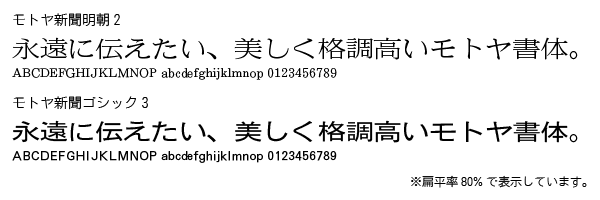
【組込み製品】モトヤARIB対応フォント発売のお知らせ(17/09/11)
モトヤの新製品「モトヤARIB対応フォント」の発売についてお知らせいたします。
株式会社モトヤでは、2017年9月11日に「モトヤARIB対応フォント」の販売を開始いたしました。
ARIB STD-B62規格は、一般社団法人電波産業会(ARIB)が策定するJIS X 0213:2004を標準文字セットとし
4K・8Kなど最新のデジタル放送向け記号・文字を追加した最新規格です。
モトヤでは、ARIBの最新規格である「ARIB STD-B62」に対応したフォントをラインナップしています。
高画質デジタル放送で読みやすく美しいモトヤフォントをご利用ください。
<書体サンプル>
| ○製品名 | モトヤARIBシーダ 3/5 モトヤARIBマルベリ 3/4 |
| JIS X0213:2004対応フォント | JIS2004対応フォントが新たにUD対応 |
| モトヤARIB対応フォント | 4K・8K対応ARIB規格STD-B62準拠フォント |
| ビットマップフォント | 組込み用UDビットマップフォント |
| モトヤフォントの導入事例 | 組込み機器などモトヤフォントの導入事例の紹介 |
モトヤLETSの新書体「アラタ2B/4/6」ダウンロード提供のお知らせ(17/08/08)
モトヤLETS会員様向けの新書体としまして、「モトヤアラタ2B/4/6」のダウンロード提供が
2017年8月22日より開始されます。
今回、提供が開始されます「モトヤアラタ」は、仮名フォント「Mkアラタ」のレトロな雰囲気はそのままに、
「Mkアラタ」が持つエレメントの特徴を持った漢字を収録し、さらに仮名をリデザインした書体です。
和文書体として帰ってきた新たな「アラタ」書体、3ウエイトの登場となります。
<書体サンプル>
○提供書体:モトヤアラタ 2B/4/6
Windows10アップデート後の不具合に関するお知らせ(17/01/05)
Microsoft社から提供されているWindows10の大規模アップデート「Anniversary Update」を適用すると、主にOpenTypeフォントでの縦組みにおいて複数のアプリケーションソフトウェアで表示や印刷で、書体が別のものに置き換わったり、縦組みの記号類が横組みになったりという不具合が発生しています。
現在のところ、回避策はありませんので、Windows10 Anniversary Updateを適用されないようにしてください。
また、適用された場合は、Windows10 Anniversary Updateを適用前のビルドに戻してください。
なお、本現象は弊社製品の問題ではなく、Windows10 Anniversary Updateに起因する問題です。